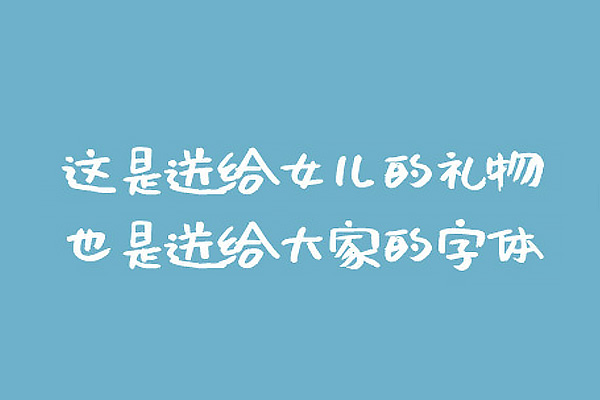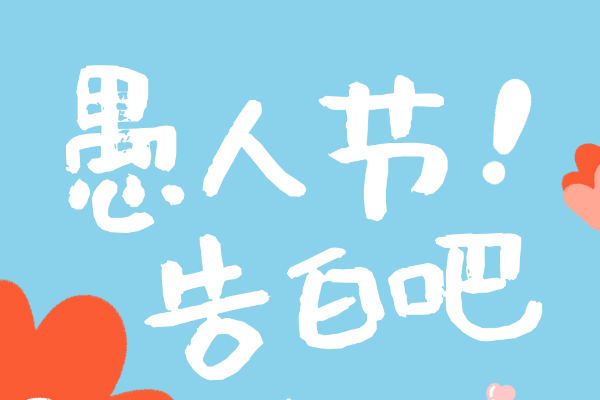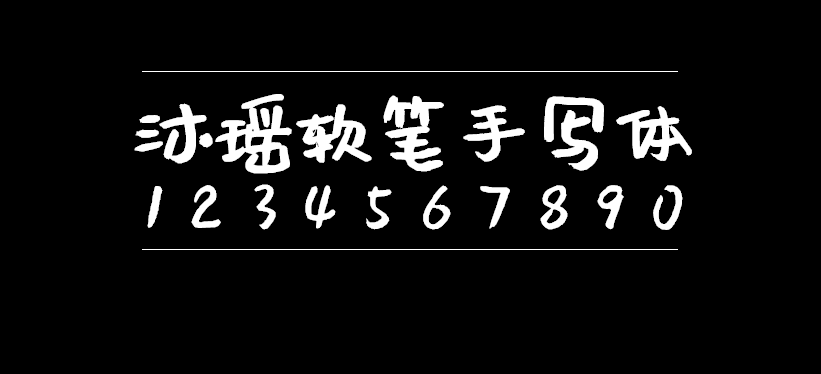
沐瑶软笔手写体
作者春颜秋色,重庆平面设计师。在从事平面设计的工作中,经常需要手写字,发现楷隶行草之类的字体较多,较为休闲可爱的字体较少,好看的几款都有较为严格的版权限制,设计师使用时需要较高的门槛。 2018年决定开工,因为七月恰好是其女儿周岁生日,就用女儿名字拼音来命名,叫做“MuYao”,字母命名是方便兼容各类软件,因为是用软头毛笔写的,全名就叫做“沐瑶软笔手写体”。 供大家免费使用(包含免费商业使用),作者仅保留字体的创作者权利。